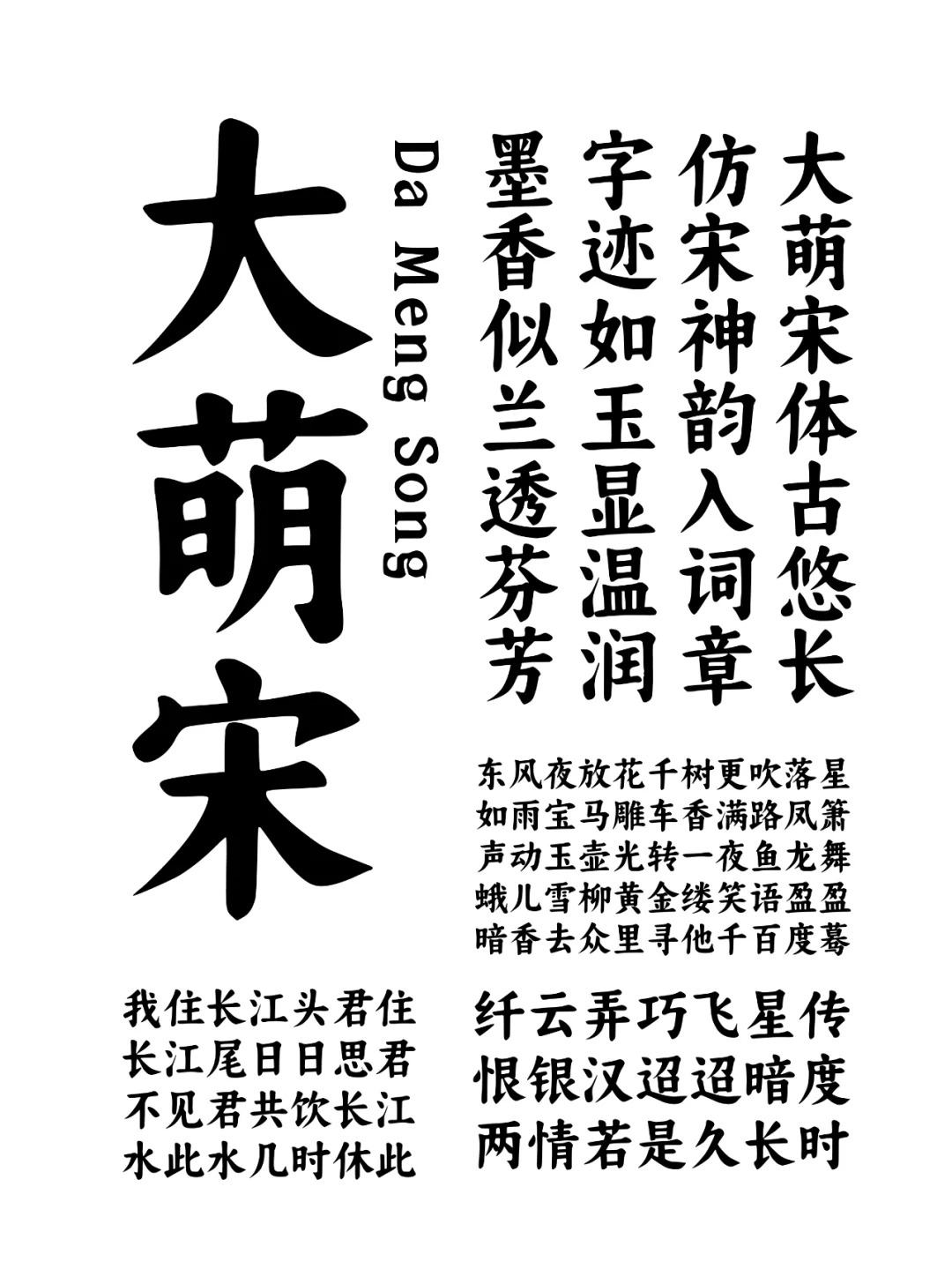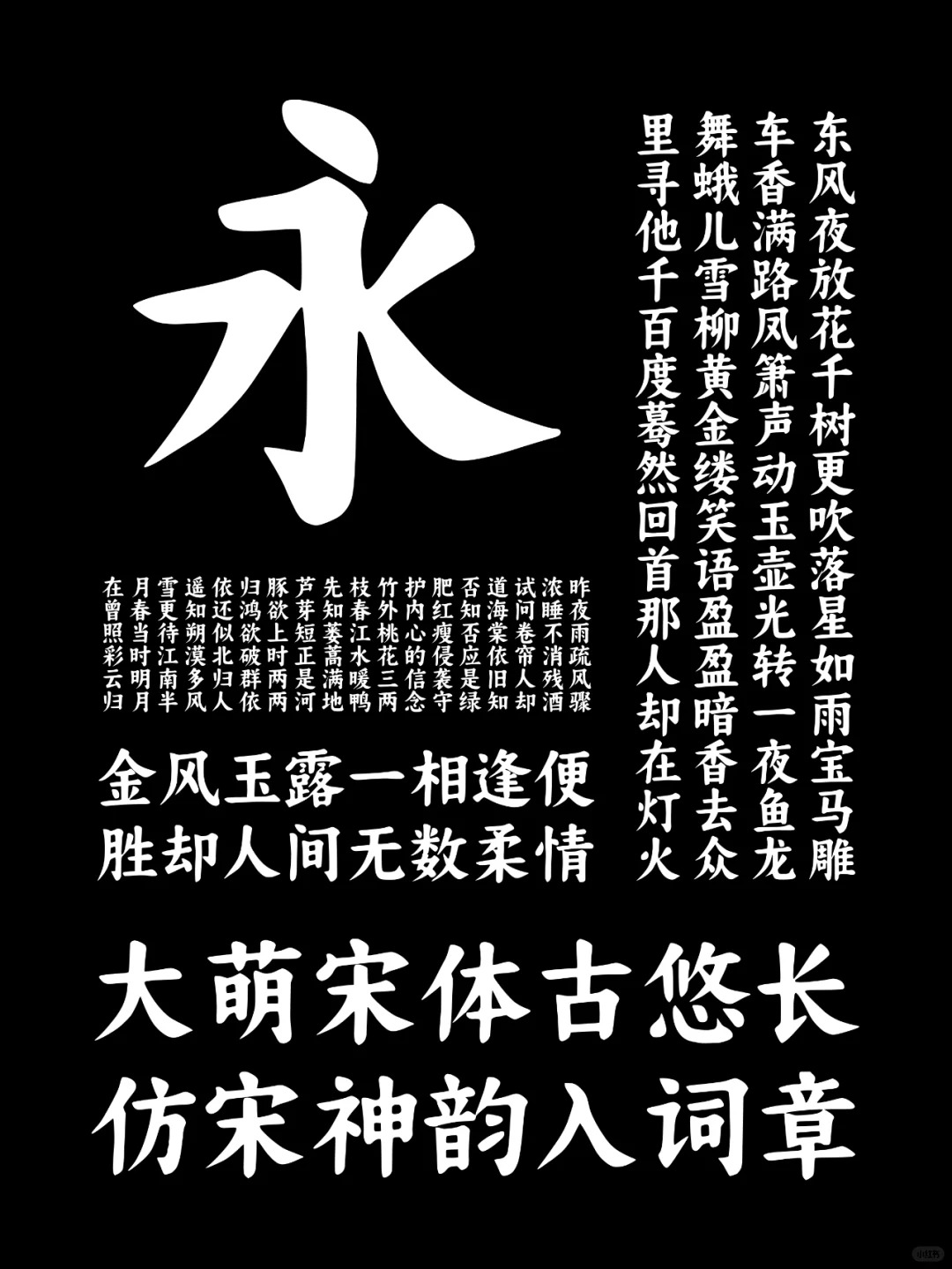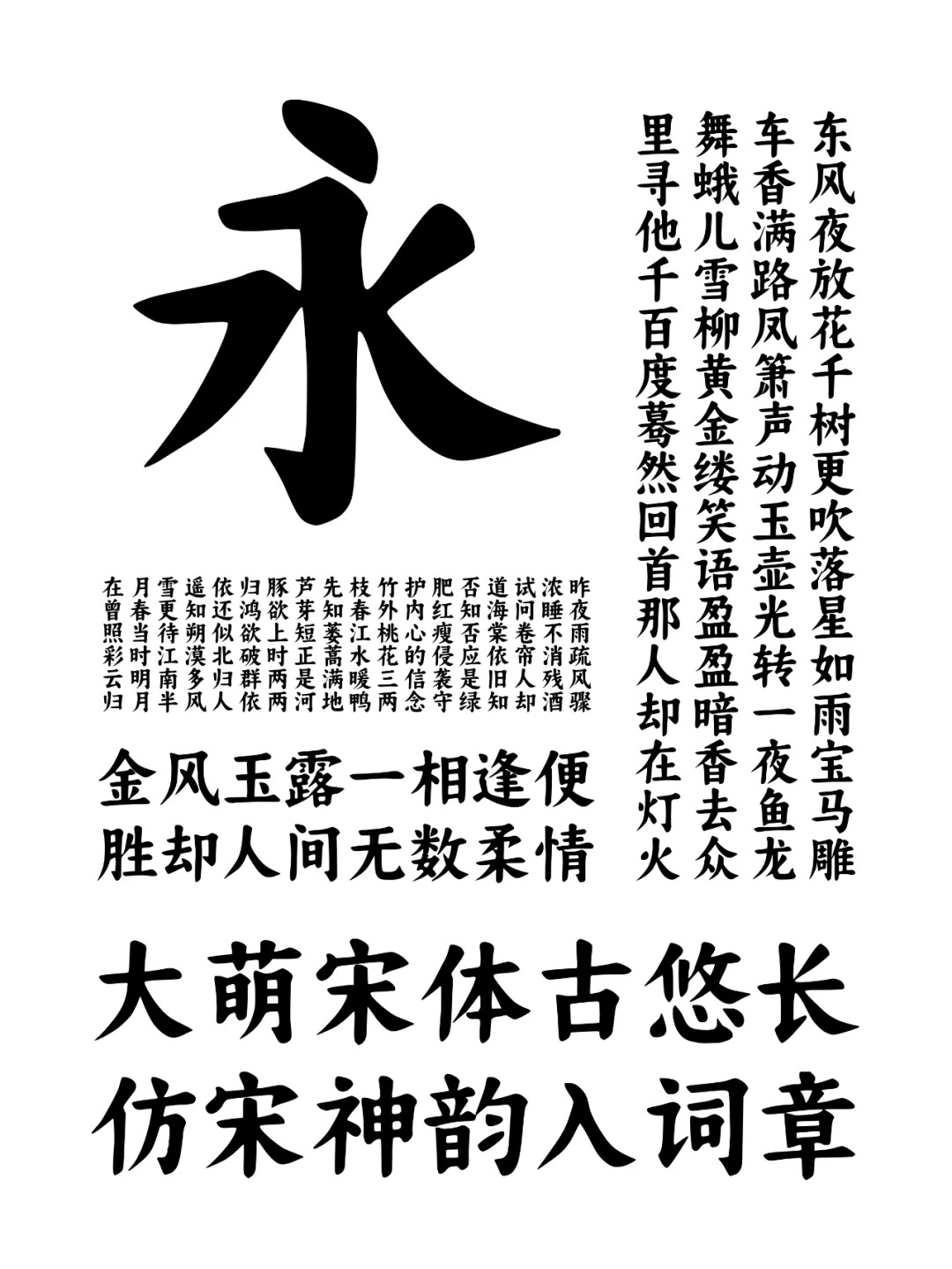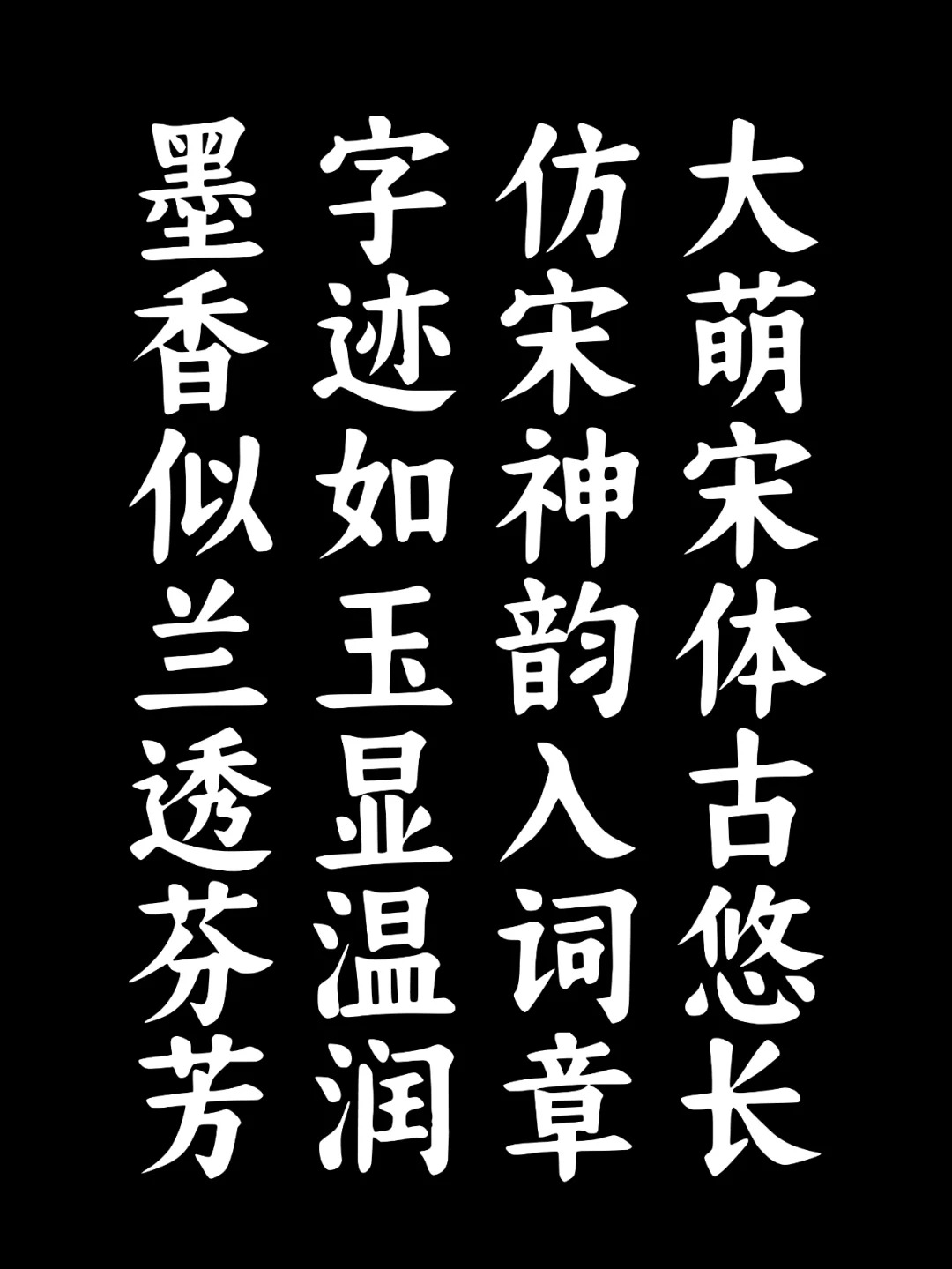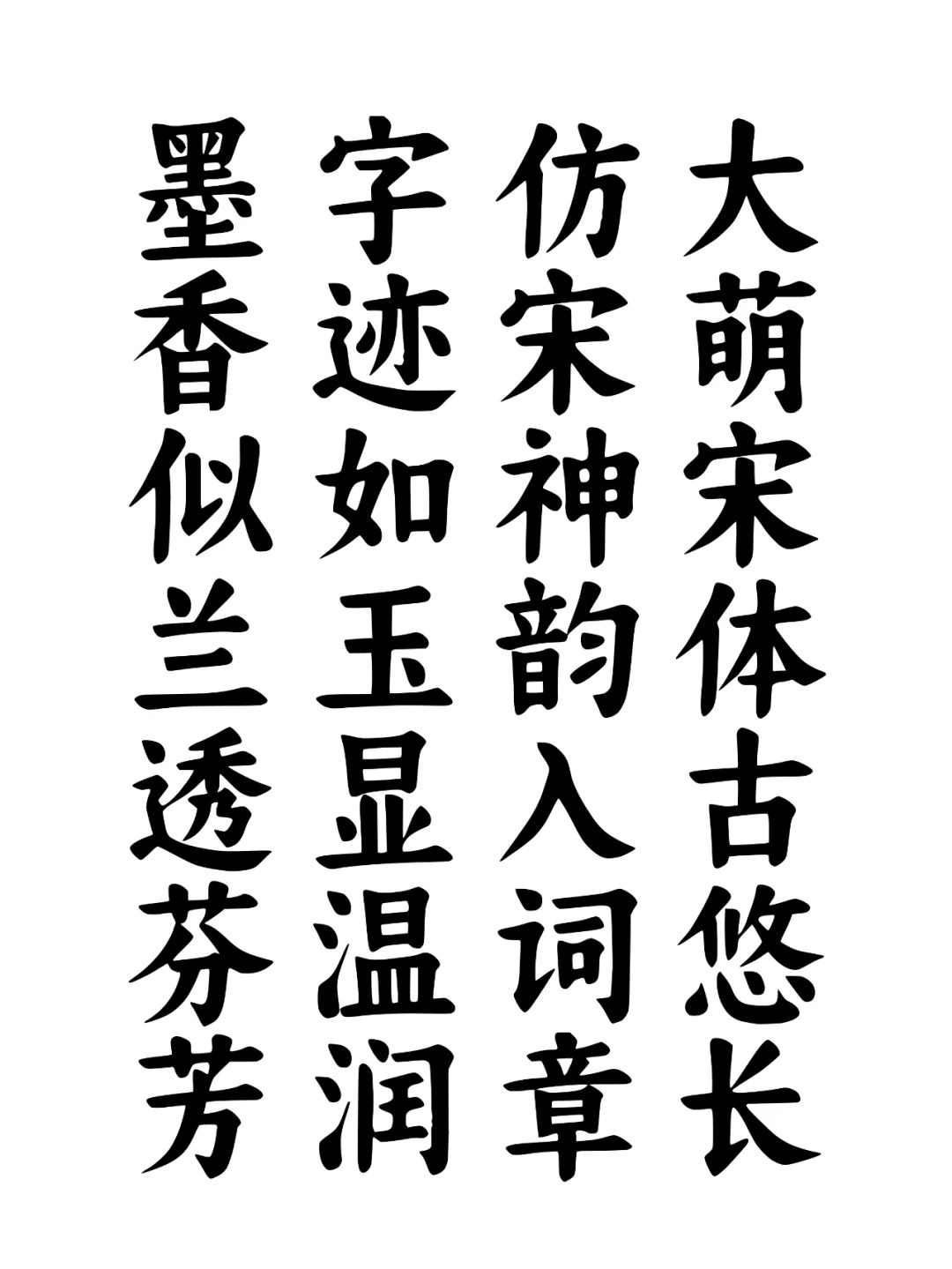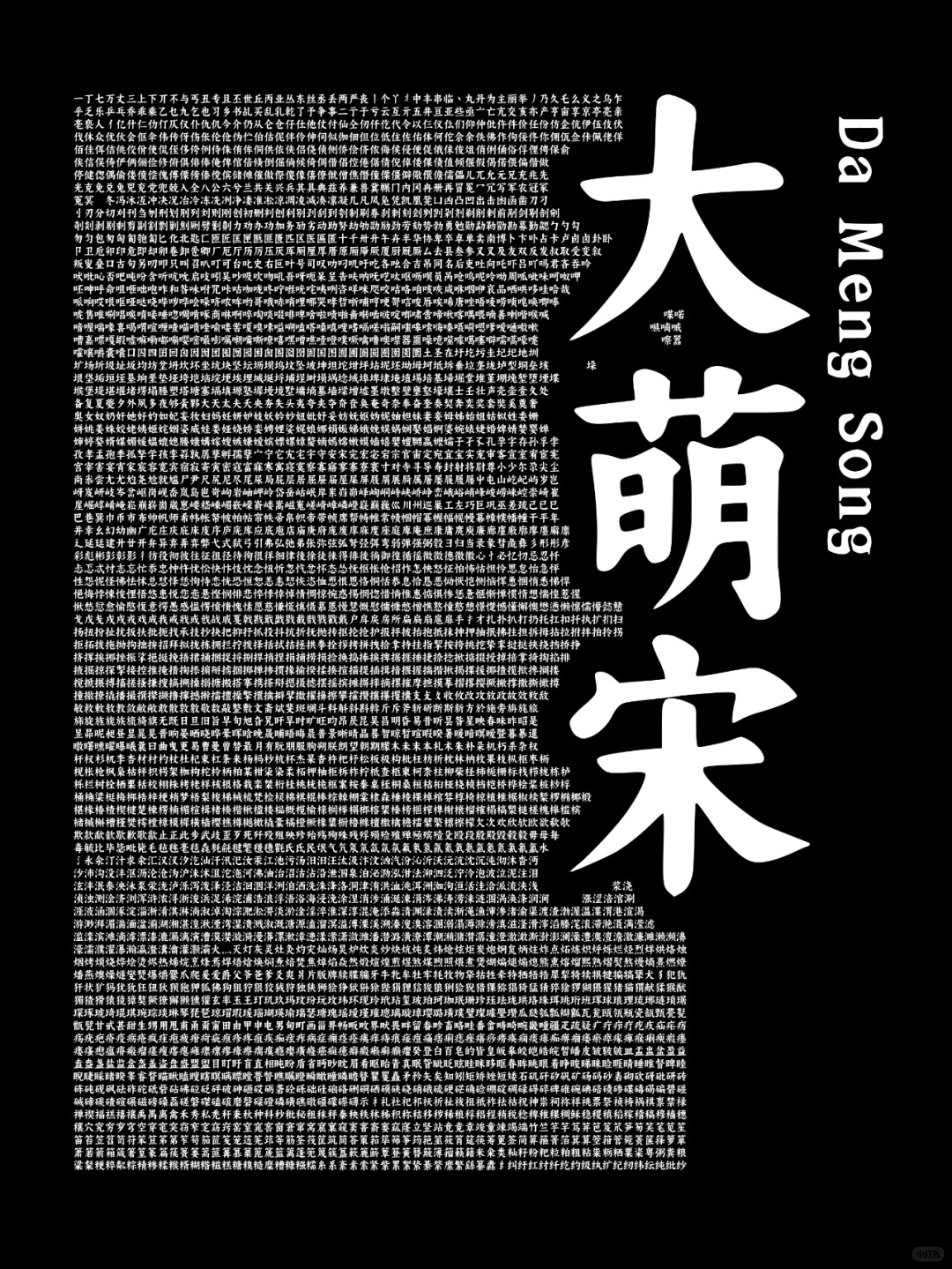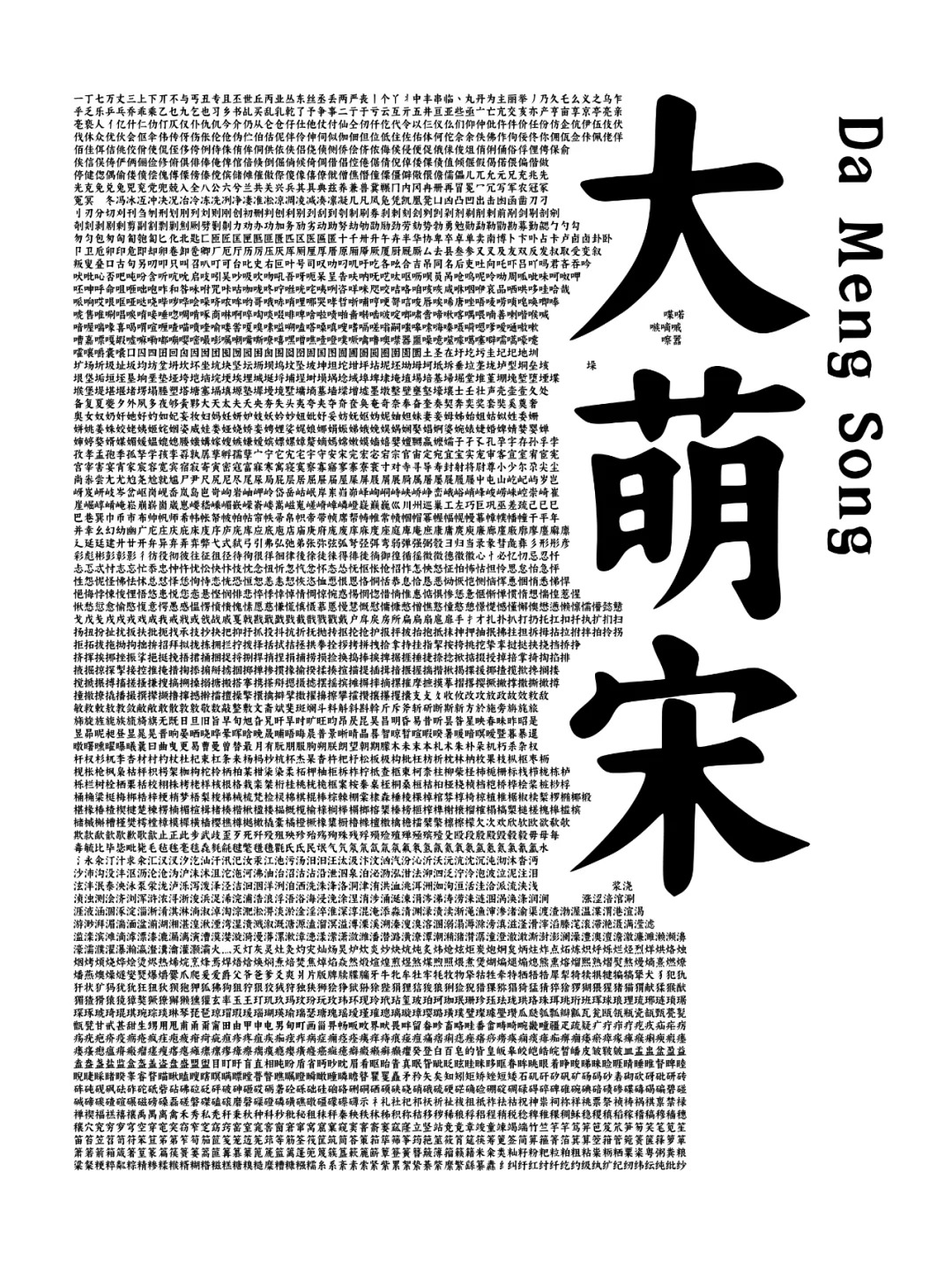
大萌宋
关于大萌宋字体字库信息
字体全名: 大萌宋
铸字厂: 小欣大萌
设计师: 曾颖欣
字体简介: 《大萌宋》是一款温润仿宋,不仅承载着历史的厚重,更在现代设计的舞台上绽放异彩。其独特的温润质感,仿佛能穿越时空,将古人的风雅与现代审美巧妙融合。【诗:大萌宋体古悠长,仿宋神韵入词章。字迹如玉显温润,墨香似兰透芬芳】